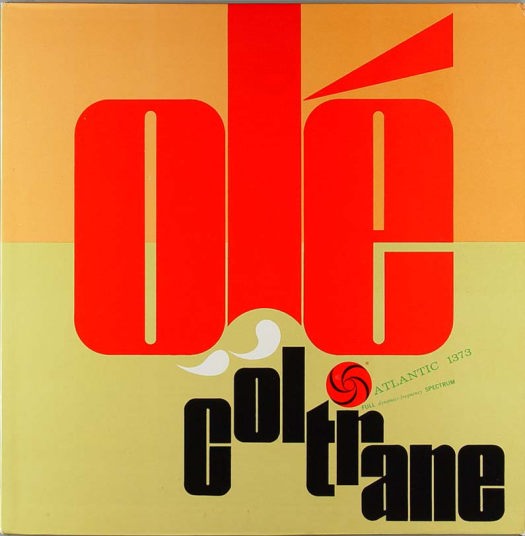
Welcher Font mag das sein?
Oder was kommt dem sehr nahe?
liebe kollegen , in 1961 (die Bleizeit) hat der Designer ( Jagel & Slutzky Graphics) wahrscheinlich die Schrift gezeichnet. Im übrigen, eine wahnsinnsbesetzung : Drums - Elvin Jones Flute - Eric Dolphy (tracks: 1, 4) Piano - McCoy Tyner, Producer - Nesuhi Ertegun Recording Engineer - Phil Ramone! Saxophone [Alto] - Eric Dolphy (tracks: 1, 4) Saxophone [saxophone] - John Coltrane ) Trumpet - Freddie Hubbard
Nach TypoLion ist das wohl keine Schrift sondern eine Grafik. Den weiteren Hintergrundinformationen nach ist das sogar sehr plausibel. Die Schrift hat mich aber ein ganz klein wenig an die Europa Grotesque erinnert:
Entfernt ähnliche Retroschriften gibt es auch bei Fontalicious:
Vielleicht können diese Schriften als Rohmaterial für Grafiken herangezogen werden?